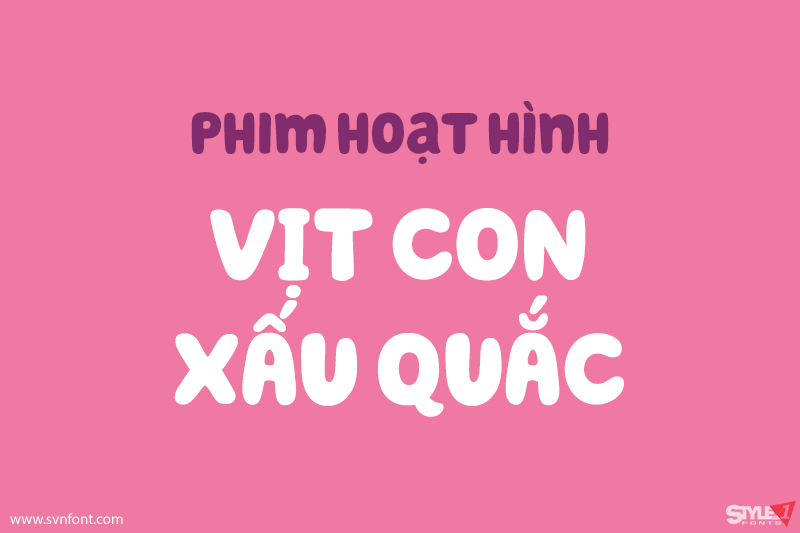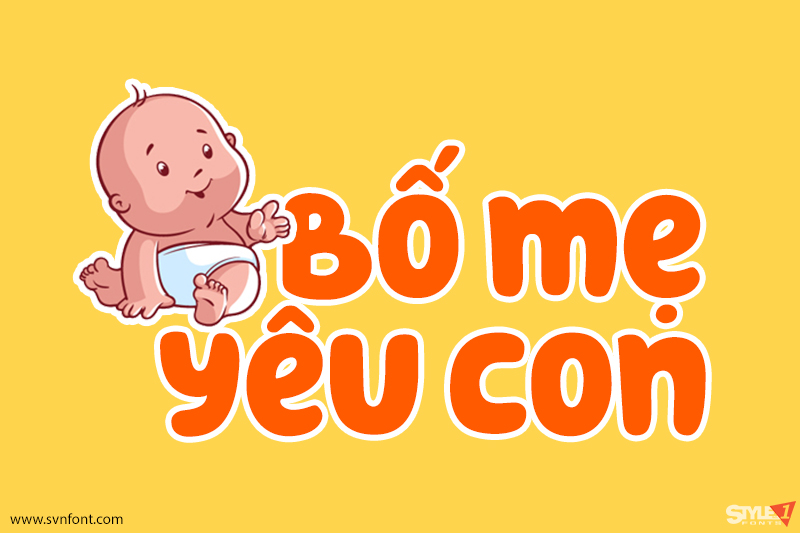
Hello Headline là một typeface đậm nét và thân thiện, được thiết kế chuyên biệt (tin hay không thì tùy) cho tiêu đề. Các ký tự đều to, tròn và chắc, vì vậy có thể nhìn rõ từ khoảng cách rất xa — thật sự là rất xa. Tổng thể font mang cảm giác thoải mái, gần gũi, nên đặc biệt phù hợp với các thương hiệu vui vẻ, cởi mở và chân thành.